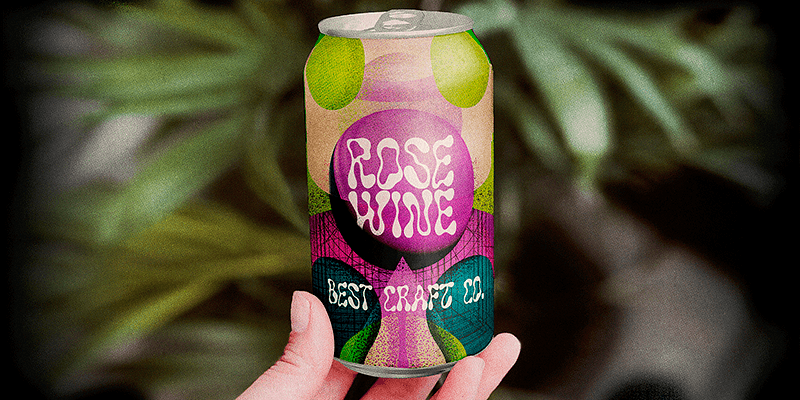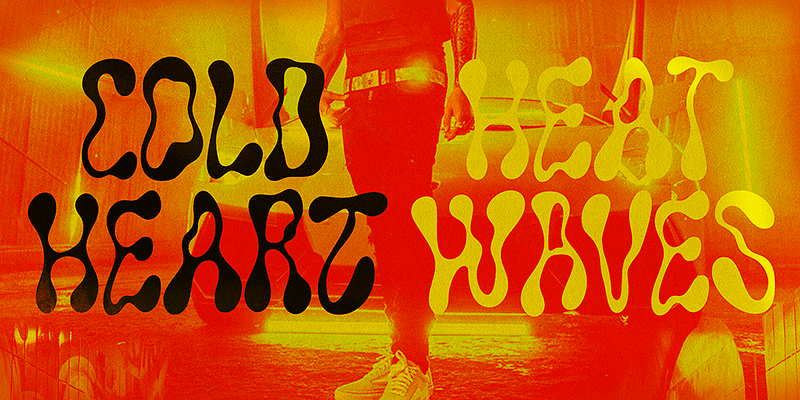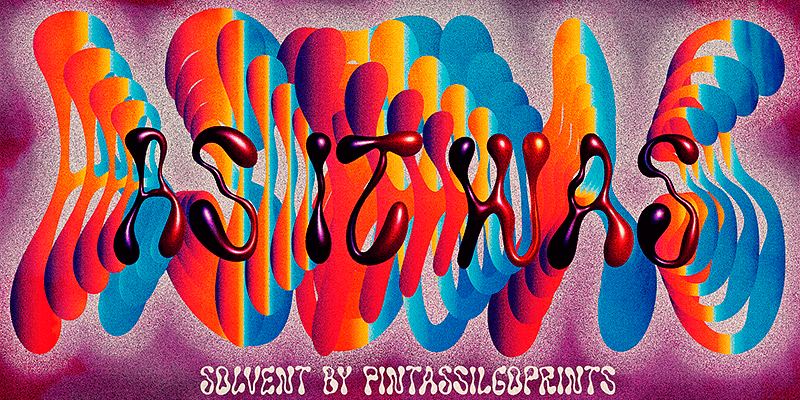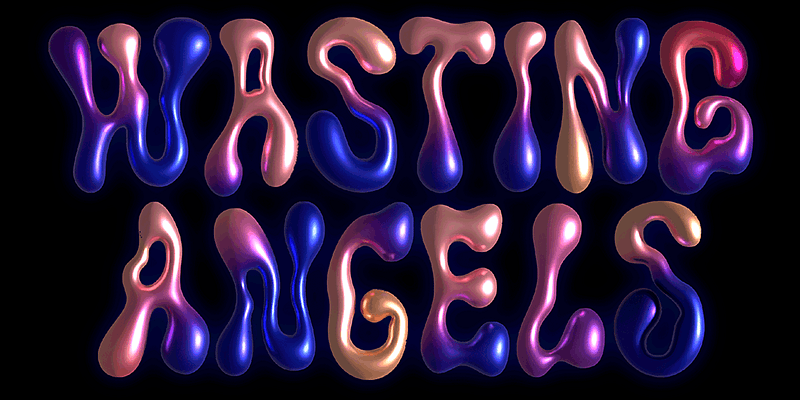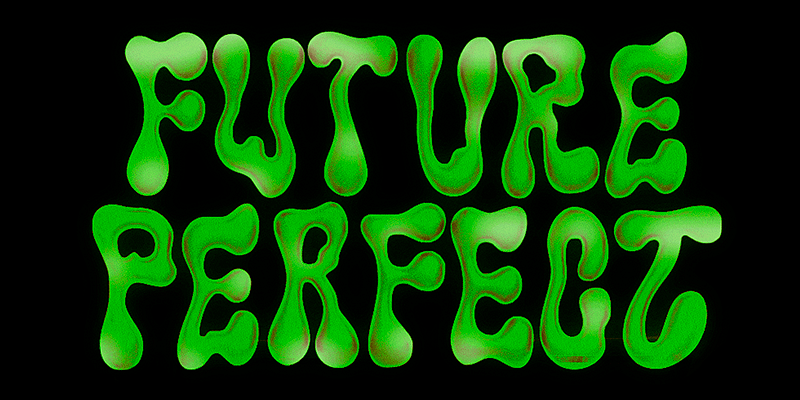
PintassilgoPrints es una casa tipográfica digital con sede en Brasil, fundada en 2009 por Erica Jung & Ricardo Marcin. Son famosos por su selección de tipos de letra manifiestamente ecléctica y artística, cada uno de los cuales se caracteriza por un estilo excepcional y una elegancia creativa. ¡Estilos de letra para invitaciones! ¡Serif para títulos! ¡Sans para carteles! Vintage y retro, caprichoso y divertido, rotulado y en caligrafía: son infinitas las oportunidades para que los creativos y diseñadores den expresividad de manera original a sus trabajos.